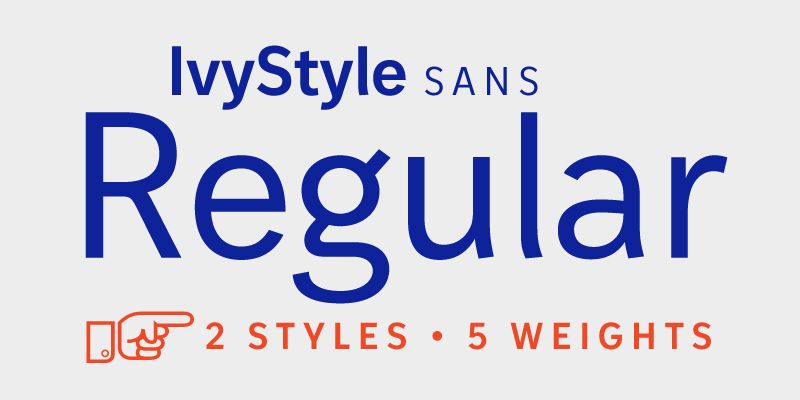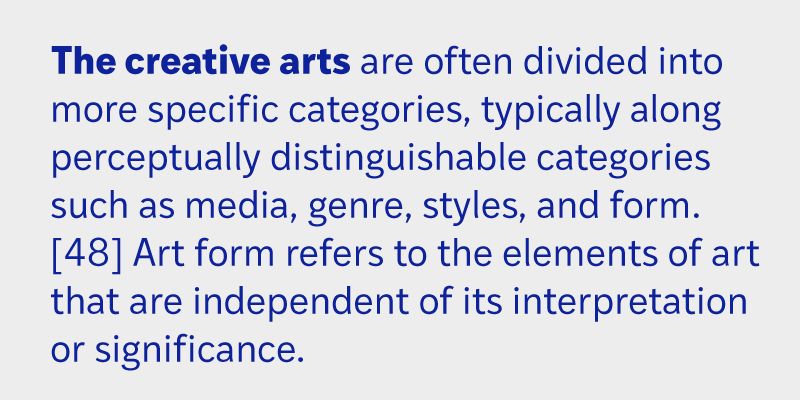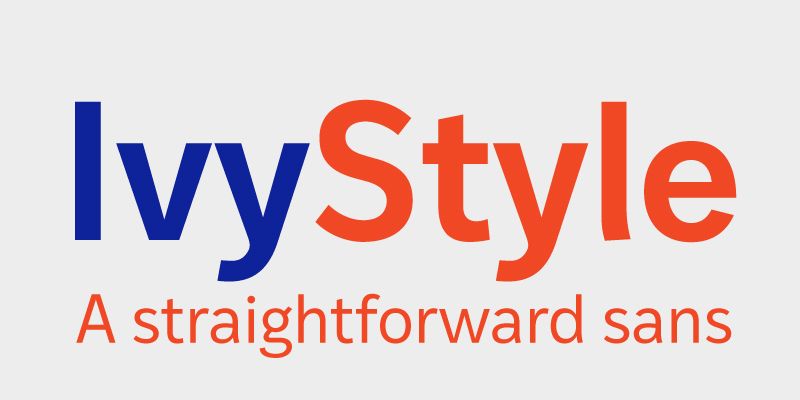
Jan Maack a insufflé au style épuré et moderne d’IvyStyle Sans la touche chaleureuse et conviviale du genre humaniste, et il a incorporé juste assez de détails originaux pour donner à cette police une personnalité unique mais discrète. Les lignes épurées et les grandes ouvertures offrent un excellent confort de lecture, tandis que ses proportions étroites permettent de gagner de l’espace, ce qui en fait une police sans serif multifonctionnelle idéalement adaptée au design éditorial, au branding et au travail d’identité. Associez IvyStyle Sans à sa sœur IvyStyle TW pour obtenir des combinaisons harmonieuses sans empattement ou avec des empattements. The Ivy Foundry, 2016.